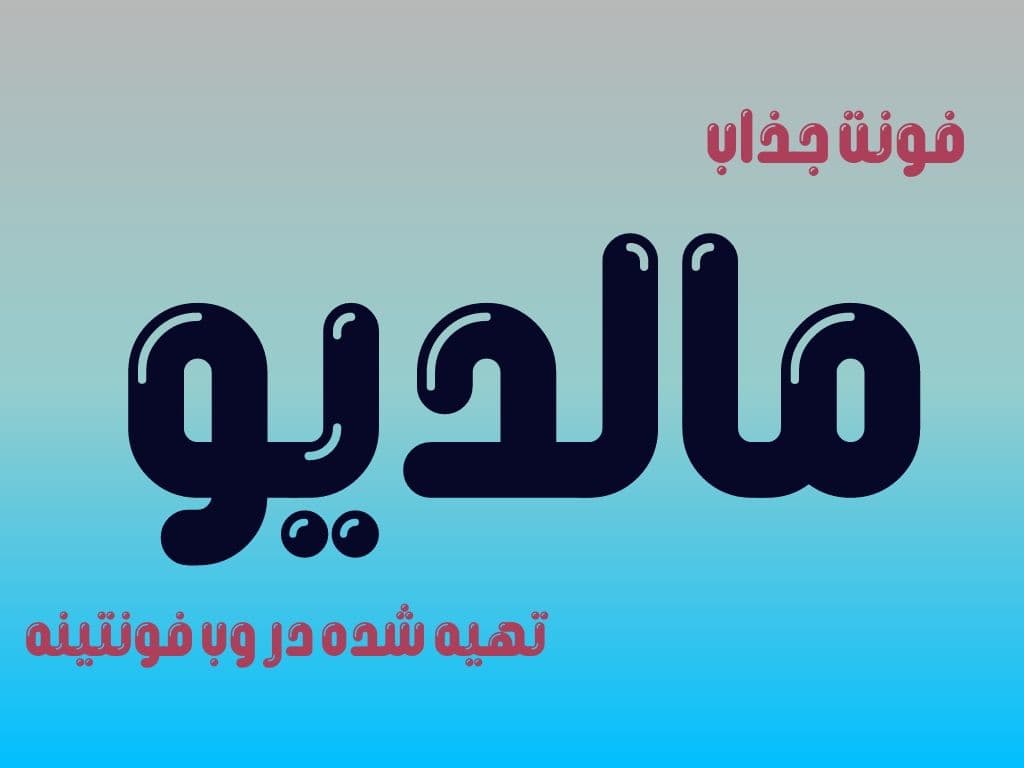
دانلود فونت مالدیو
دانلود فونت مالدیو در خدمت شما بزرگورارن هستیم با ارائه فونت زیبا و فارسی مالدیو این فونت برای طراحی های لوگو و بنر و…. مورد استفاده قرار میگیرد.
ویژگی های فونت مالدیو :
• مدرن و کاربردی
• زیبا و خاص
• مناسب طراحی لوگو و بنر
تصاویری زیبا از طراحی های خاص با فونت مالدیو که برای نمایش و نمونه پیش فرضی از نمایش این فونت کاربردی طراحی شده است